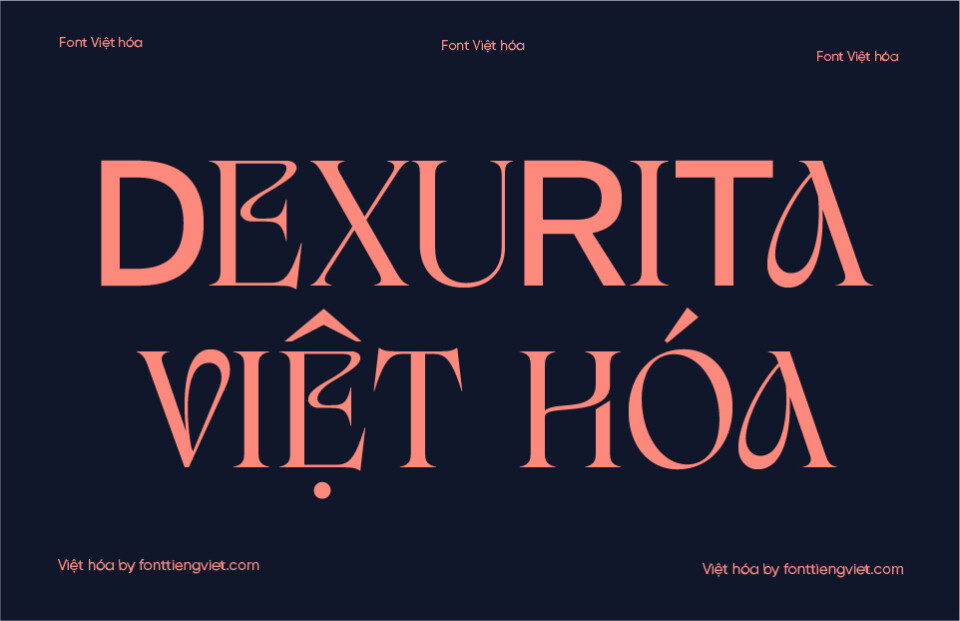
Font Việt hóa 1FTV Dexurita
Font Việt hóa 1FTV Dexurita – Font chữ thanh lịch và độc đáo dành cho thiết kế học đường
Giới thiệu về Font Việt hóa 1FTV Dexurita
Trong thế giới sáng tạo, việc lựa chọn một Font Miễn Phí chất lượng là yếu tố then chốt giúp các bài thuyết trình hay báo tường trở nên ấn tượng. Font Việt hóa 1FTV Dexurita nổi lên như một lựa chọn hoàn hảo nhờ sự kết hợp tinh tế giữa nét chữ hiện đại và phong cách cổ điển. Đây là bộ font được tinh chỉnh kỹ lưỡng để phù hợp với bảng mã tiếng Việt, giúp người dùng không còn lo lắng về lỗi hiển thị dấu khi soạn thảo nội dung học thuật hay trang trí nghệ thuật.
Ưu điểm nổi bật của Font Việt hóa 1FTV Dexurita
Thiết kế mềm mại và dễ đọc
Đặc điểm nhận dạng của Font Việt hóa 1FTV Dexurita chính là những đường nét bo tròn mềm mại nhưng vẫn giữ được cấu trúc chắc chắn. Điều này tạo nên cảm giác dễ chịu cho mắt người xem, cực kỳ phù hợp cho các em học sinh dùng để làm tiêu đề bài tập lớn hoặc các thầy cô giáo thiết kế giáo án điện tử sinh động. Font chữ này không chỉ đẹp mà còn mang tính ứng dụng cao trong nhiều môi trường khác nhau.
Tính linh hoạt trong ứng dụng thực tế
Kết luận và trải nghiệm Font Việt hóa 1FTV Dexurita